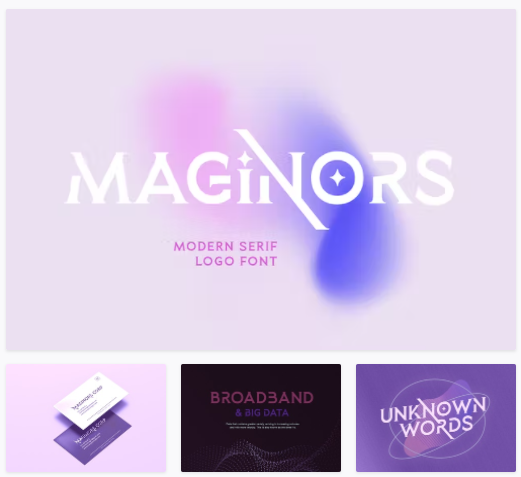
[Elements.Envato] Maginors Font (2022)
[elements.envato] Maginors Font (2022)
Maginors - это шрифт с засечками и уникальными строчными буквами, благодаря которому ваш дизайн будет выглядеть стильно и современно. С помощью волшебного штриха этот шрифт сделает ваш проект потрясающим и волшебным. Вы можете использовать этот шрифт для любых целей, особенно для создания логотипа. Вы можете смешивать и сочетать прописные и строчные буквы, чтобы сделать ваш логотип более особенным. Этот шрифт также имеет специальные чередования, которые сделают ваш дизайн более выделяющимся!